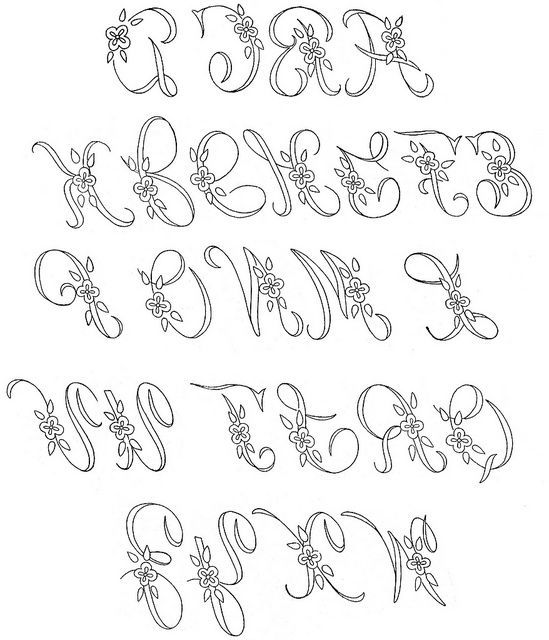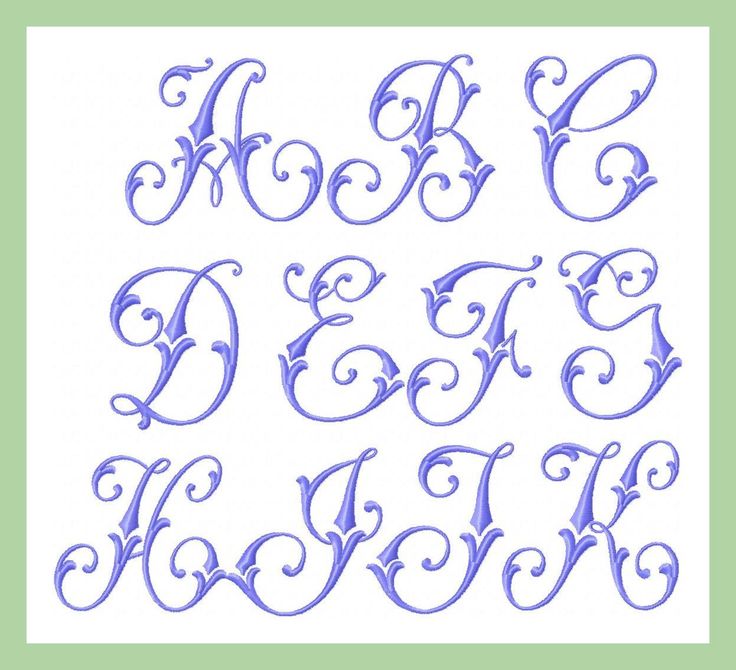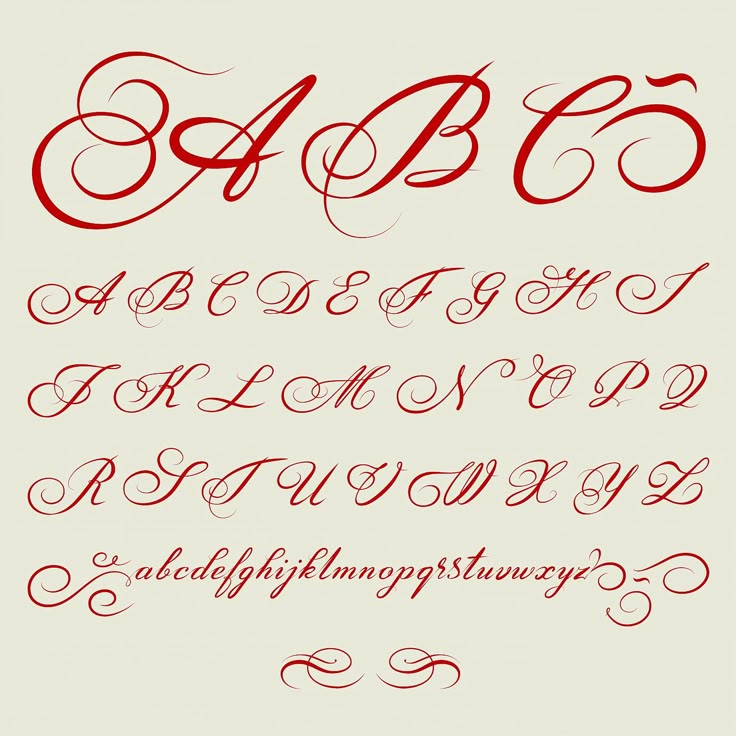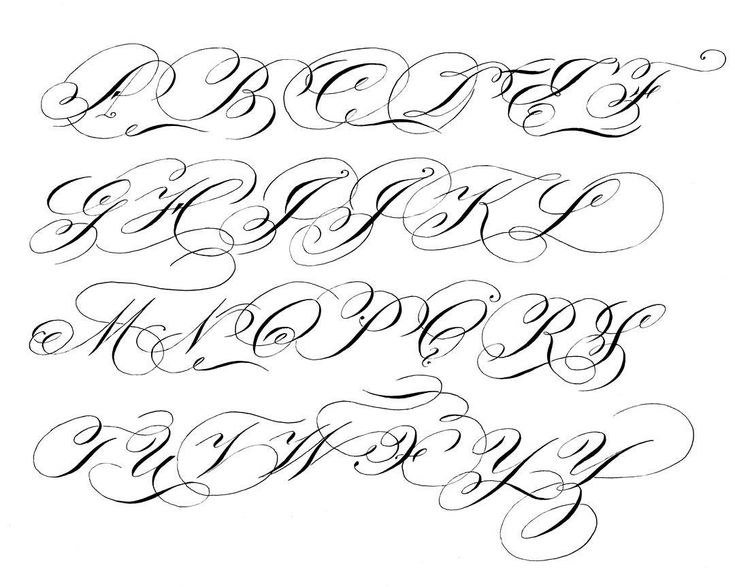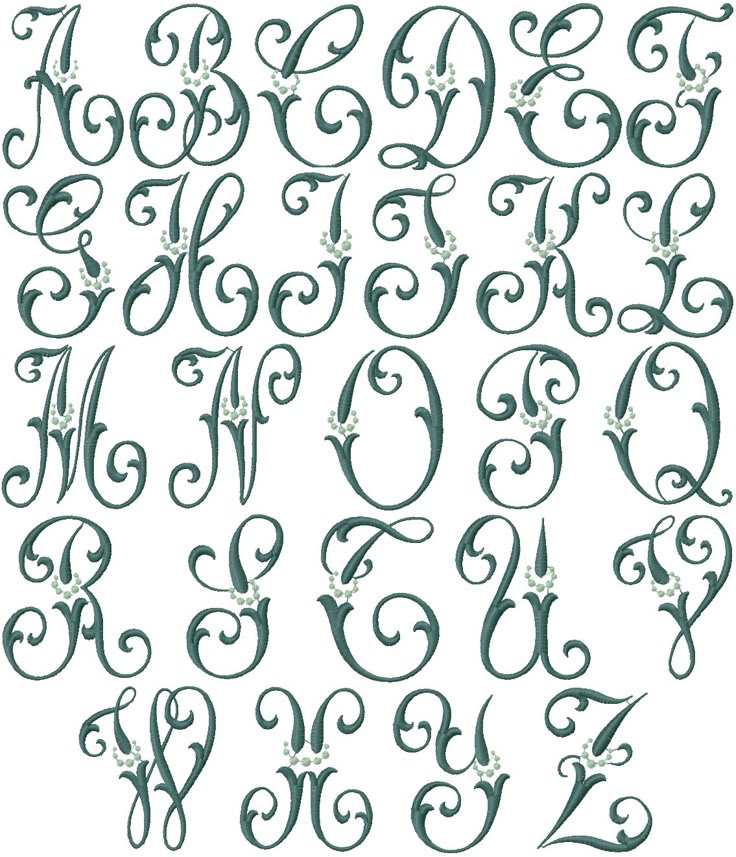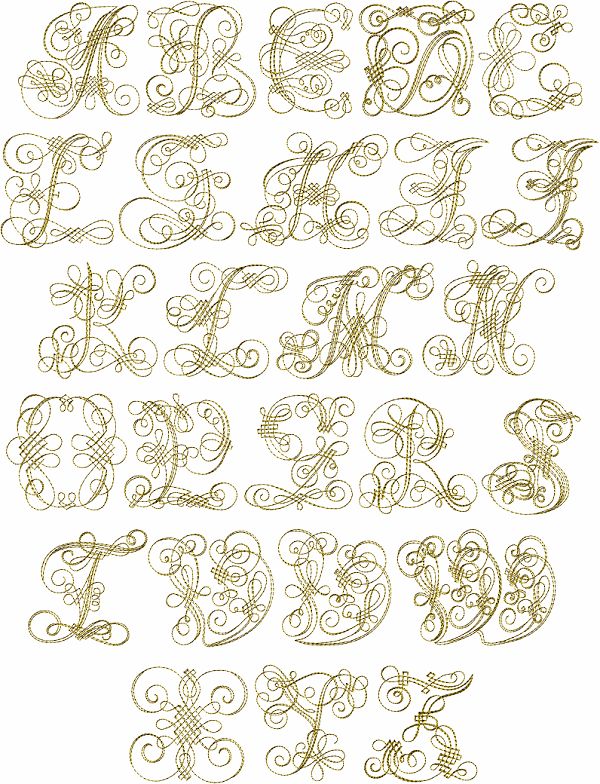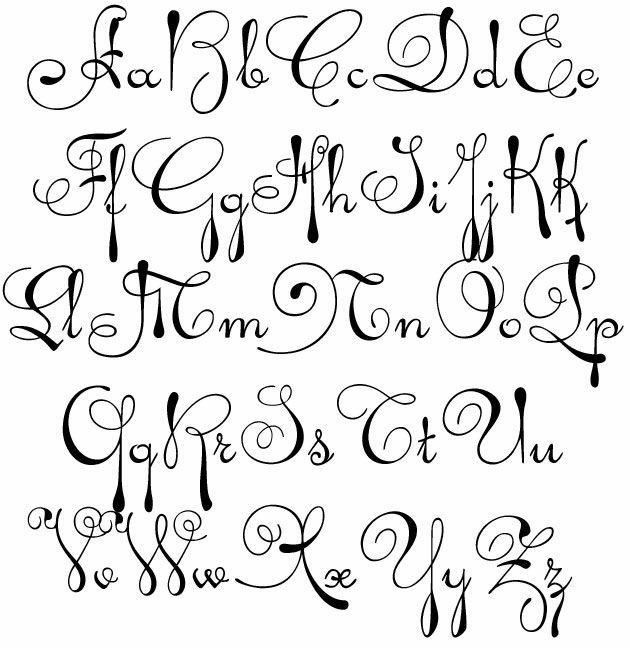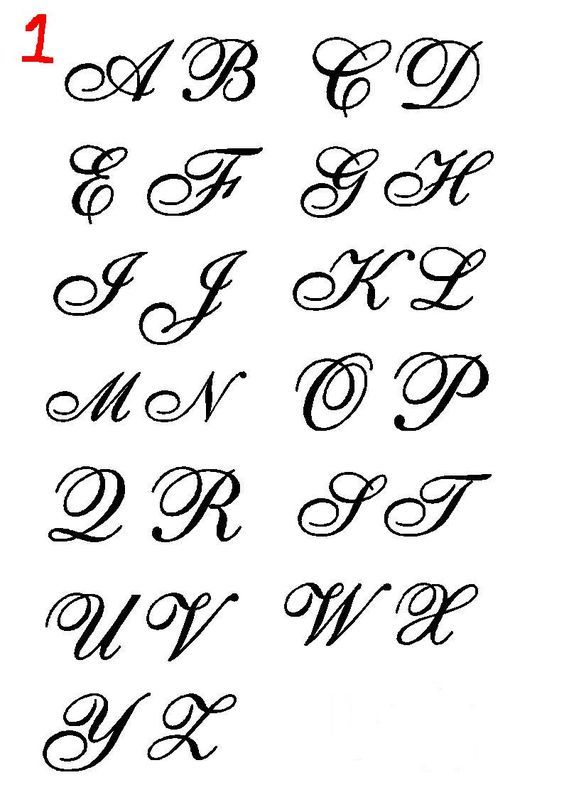
Как называется красивый шрифт с завитками: Шрифты с завитушками
10 красивых рукописных шрифтов
Одна из составляющих успешного дизайна — удачно подобранная гарнитура. Мы собрали 10 красивых рукописных шрифтов в открытом доступе, которые можно использовать для заголовков разных уровней.
Частая боль веб-дизайнеров — подбор удачных шрифтов для заголовков страниц, которые и настроение бренда, дизайна передадут, и читаться будут хорошо, и в общую концепцию отлично впишутся. Собрали в одну подборку те решения, которыми пользуемся сами и те, которые вы вряд ли видели раньше.
Brayline
Отлично смотрится как рядом с мелкими деталями, так и на чистом, однотонном фоне.
Его даже можно использовать при разработке фирменного стиля (например, завитки могут стать независимым элементом дизайна и использоваться отдельно для создания концепта).
Шрифт подойдет для проектов, где важно передать брутальность, мужественность и строгость — то есть тех, где целевая аудитория — молодежь либо парни, мужчины.
Anthares
Отличается якобы небрежными завитками в первой и последней буквах слова. Хорошо смотрится с другими рукописными шрифтами (только с печатными знаками).
Подойдет для проектов, где важна аутентичность, свобода, легкая небрежность и безрассудность в действиях. Его хорошо воспримут молодежь, подростки.
Marguaritas
Шрифт, который передает легкость, ощущение романтики и расслабленность как с тонким, так и с жирным начертаниями. Лучше смотрится и читается с короткими словами. Подойдет для проектов, связанных с отдыхом, поездками на острова, женскими каталогами одежды или платьев, романтическими услугами.
The Zains
Шрифт, который ассоциируется с легкой, спокойной музыкой (джазом), романтическим настроением, танцами, искусством. Несмотря на сильный уклон вправо, читается хорошо, даже если его использовать для фразы из нескольких слов.